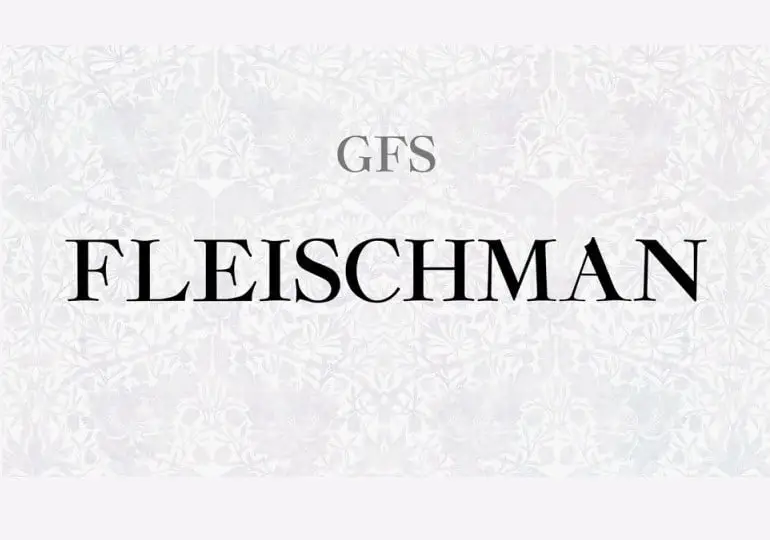
GFS Fleischman Serif é uma elegante tipografia serifada ideal para projetos que valorizam a simplicidade e sofisticação ao mesmo tempo. Esta fonte, criada pela Greek Font Society, oferece um conjunto completo de caracteres normais e combina o contraste marcante típico das serifas em design moderno com os detalhes mais refinados do barroco da década de 1700. É perfeitamente adaptável para aplicações variadas que buscam uma harmonia entre minimalismo e estilo clássico, tornando-a uma escolha irresistível tanto para aplicativos digitais quanto impressos. GFS Fleischman Serif é a fonte ideal para quem busca um equilíbrio perfeito entre modernidade e elegância no seu design de marca ou em projetos gráficos.